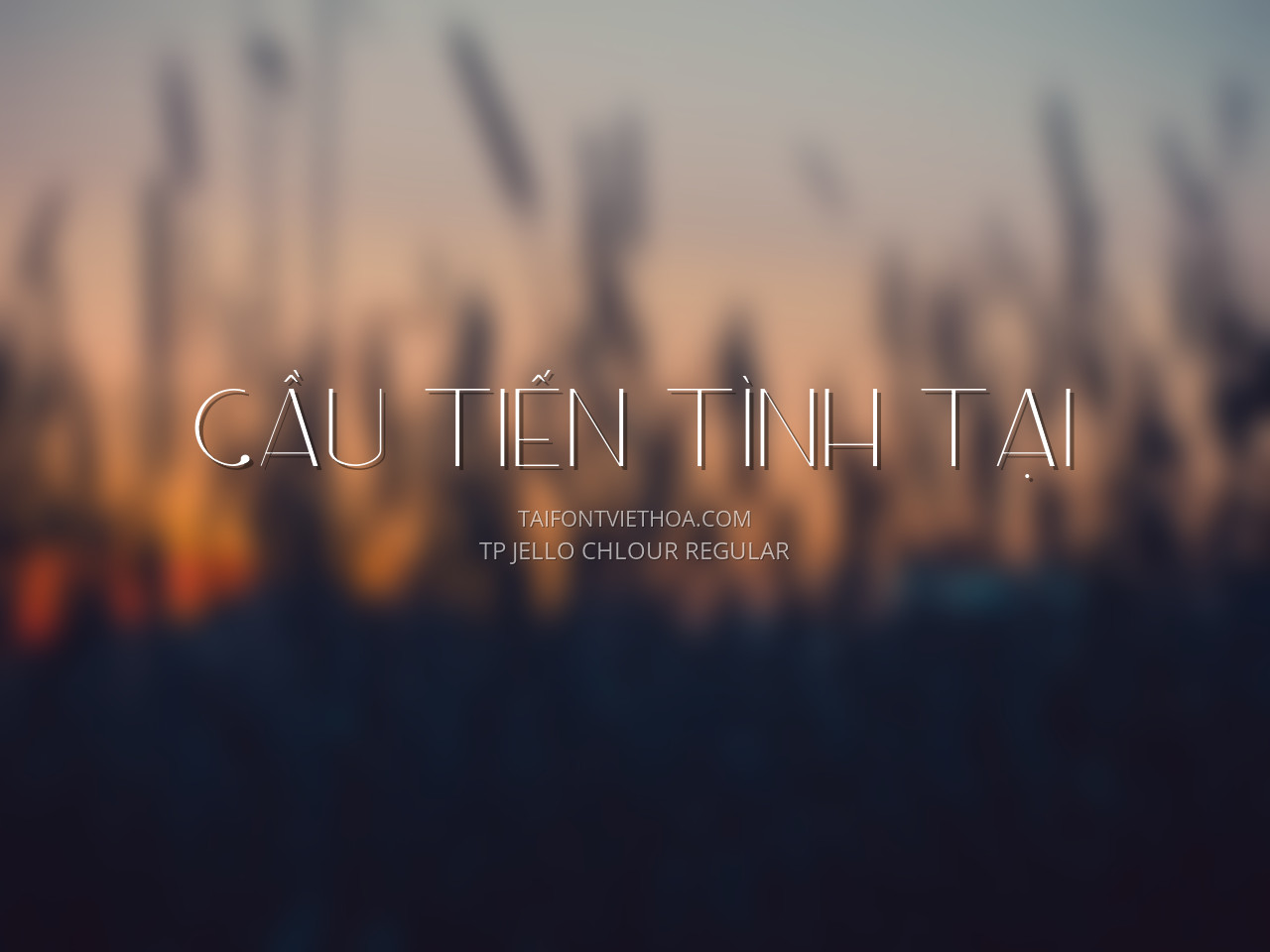
Font việt hóa TP Jello Chlour
Giới thiệu về font TP Jello Chlour – Kiểu chữ decorative độc đáo, năng động và hiện đại
TP Jello Chlour là phiên bản Việt hóa của font Jello Chlour – một kiểu chữ decorative mang phong cách độc đáo, năng động và rất hiện đại. Font được thiết kế với các nét chữ sáng tạo, mềm mại và nhiều chi tiết bắt mắt, phù hợp cho các dự án thiết kế poster, banner, thương hiệu và truyền thông kỹ thuật số.
Phiên bản Việt hóa của TP Jello Chlour đã được Taifontviethoa.comchăm sóc kỹ lưỡng, hỗ trợ đầy đủ dấu tiếng Việt cùng nhiều ngôn ngữ khác. Font giúp các nhà thiết kế dễ dàng áp dụng trong các dự án sáng tạo đậm chất cá tính và ấn tượng.
Thiết kế decorative sáng tạo – Lý tưởng cho dự án thương hiệu và quảng cáo
TP Jello Chlour sở hữu các nét chữ mềm mại, độc đáo với các đường cong và chi tiết tinh tế, tạo cảm giác năng động, thu hút và bắt mắt. Font rất phù hợp cho tiêu đề, logo, poster hoặc các phần thiết kế cần điểm nhấn đặc biệt và phong cách hiện đại. Phong cách thiết kế của Jello Chlour rất thích hợp với các dự án truyền thông, quảng cáo và thương hiệu trẻ trung, sáng tạo.
Ứng dụng lý tưởng: thiết kế poster, banner quảng cáo, nhận diện thương hiệu, bìa sách, thiệp mời và các dự án sáng tạo cần phong cách nổi bật, hiện đại. Ngành nghề phù hợp: quảng cáo, truyền thông, giải trí, thương hiệu và sự kiện.